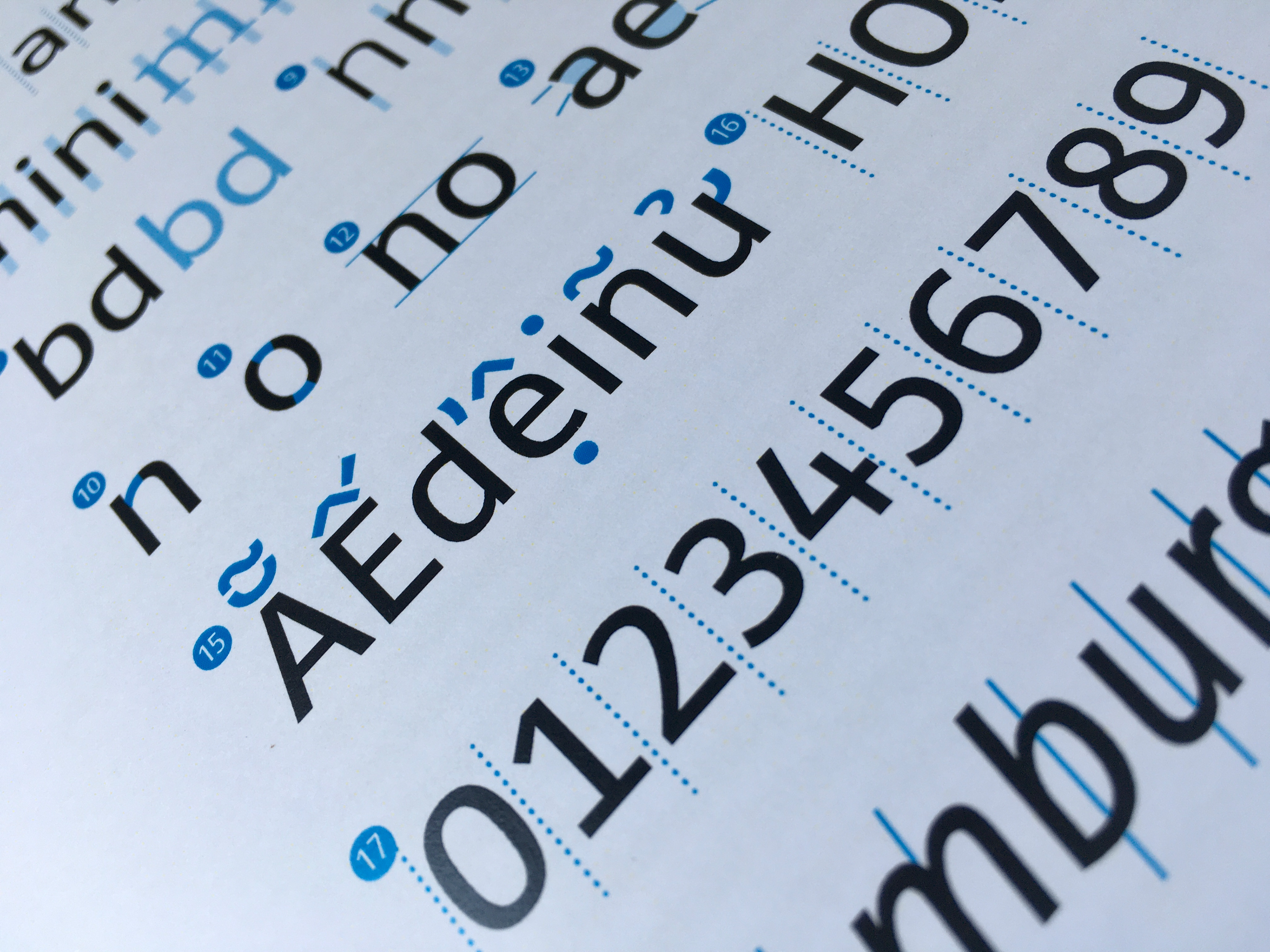
Kompleksowe rozwiązania w obszarze informacji wizualnej integrują nierzadko różnego typu przekazy – od wskazówek dotyczących poruszania się po nieznanym terenie, po komunikaty mające pomóc w wykonaniu określonych czynności. Systemy informacyjne mogą ponadto wykorzystywać różnorodne media: oznakowanie w przestrzeni, nośniki drukowane i cyfrowe (drogowskazy, mapy, przewodniki).
Wymienione obszary są silnie zróżnicowane pod względem wykorzystania środków typograficznych oraz technologii reprodukcji. Wykazują jednak punkty zbieżne w kluczowych kwestiach dotyczących potrzeb, na jakie powinien odpowiadać krój pisma mogący znaleźć w nich zastosowanie. Schematy, wykresy, graficzne interfejsy użytkownika oraz oznakowanie w przestrzeni wymagają zachowania zarówno ekonomii składu, jak i wysokiej czytelności tekstu.
Mimo właściwego opracowania na poziomie makrotypograficznym, czytelność tekstu bywa obniżana przez charakterystykę formalną zastosowanego w nim kroju pisma. Prócz kwestii związanych z nieodpowiednim wykorzystaniem pisma – niedostosowaniem wielkości, rozświetlenia, grubości, czy kontrastu jasności lub kontrastu chromatycznego tekstu i tła – obniżenie czytelności może wynikać z nieodpowiedniego rysunku znaków.
Możliwie precyzyjny opis warunków odbioru jest w tym kontekście szczególnie istotny. Nie istnieje bowiem jeden zestaw cech zapewniających czytelność kroju pisma niezależnie od okoliczności, w jakich ma przebiegać lektura. Kluczową rolę w dostosowaniu kroju do danego sposobu użycia odgrywa szereg elementów, takich jak: proporcje znaków i świateł międzyliterowych, rytm, zróżnicowanie kształtów liter, szerokość apertur, grubość pisma, czy też zastosowane korekty optyczne.
Jako sposób odpowiedzi na kluczowe potrzeby związane z zapewnieniem czytelności komunikatów tekstowych, projektowanych jako składowe systemów informacji wizualnej, wybrano opracowanie rodziny krojów pisma. Projekt ma za zadanie spełniać wymagania różnorodnych obszarów implementacji, które wchodzą w skład rozbudowanych systemów informacyjnych. Szczególny nacisk położono na problemy dotyczące podnoszenia czytelności liter i słów, z uwzględnieniem aspektów sensorycznych procesu czytania oraz wpływu zmiennych środowiskowych i technologii reprodukcji na łatwość, z jaką rozpoznawane są kształty znaków.
Decyzje projektowe zostały oparte o analizę obecnego stanu wiedzy w zakresie czytelności pisma. Określono również możliwości i ograniczenia percepcji wzrokowej, które mogą dotyczyć odbiorców projektu. Wykonano także charakterystykę elementów składowych systemów informacji wizualnej, z uwzględnieniem warunków ich technicznej reprodukcji. Wyniki analiz oraz wiedza w obszarze czytelności zostały następnie przyjęte za podstawę dla kształtowania form znaków i poszczególnych parametrów kroju.​​​​​​​
Zaprojektowana rodzina krojów występuje w pięciu odmianach szerokości oraz sześciu odmianach grubości, w antykwie i w kursywie. Ponadto przygotowane zostały odmiany do składu tekstu w pozytywie i w negatywie, by zapewnić porównywalną grubość optyczną tekstów składanych na jasnym i na ciemnym tle. Łącznie na rodzinę składa się sto dwadzieścia odmian pisma.
Krój obsługuje szeroki zakres języków zapisywanych alfabetem łacińskim, w tym wszystkie języki europejskie, język wietnamski i większość języków afrykańskich. Wszystkie odmiany w ramach rodziny krojów obejmują również rozbudowany zestaw znaków niealfabetycznych – znaki matematyczne, znaki walut oraz zestawy strzałek.
Opracowana rodzina krojów ma za zadanie odpowiadać na konkretne potrzeby w zdefiniowanych obszarach użycia pisma. Celem jej powstania jest pomoc w rozwiązywaniu najczęściej występujących problemów, które mogą dotyczyć czytelności komunikatów tekstowych na poziomie kształtowania obrazów liter i słów. Środkiem do realizacji tego celu jest zestaw starannie skonstruowanych narzędzi, które mogą być wykorzystane zarówno do budowania prostych komunikatów, jak i złożonych struktur typograficznych.
Książka Czytelność krojów pisma w systemach informacji wizualnej oraz rodzina krojów pisma Site to elementy rozprawy doktorskiej, przygotowanej na Wydziale Grafiki i Komunikacji Wizualnej Uniwersytetu Artystycznego im. Magdaleny Abakanowicz w Poznaniu. Autor: Robert Jarzec. Promotor: prof. dr hab. Krzysztof Kochnowicz. Recenzenci: dr hab. Ewa Satalecka, prof. PJATK, dr hab. Jacek Mrowczyk, prof. ASP w Katowicach.